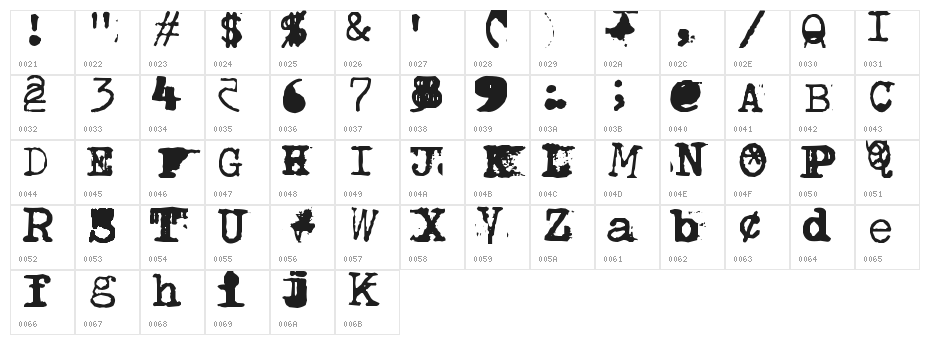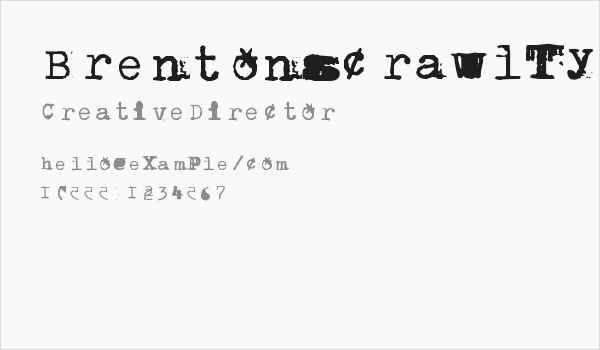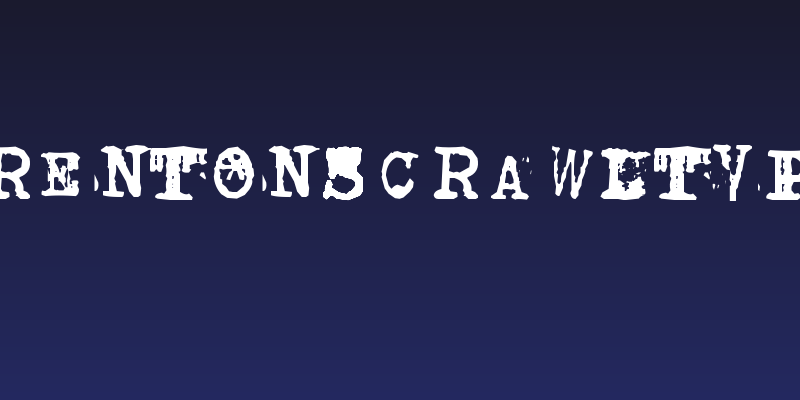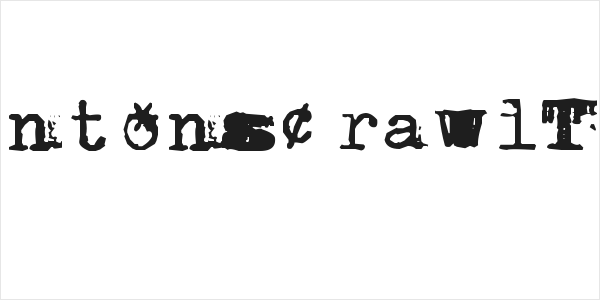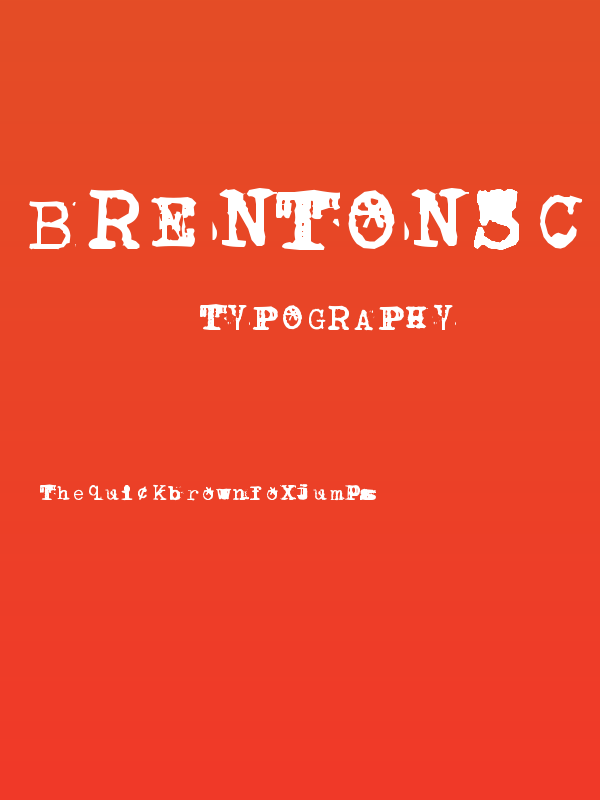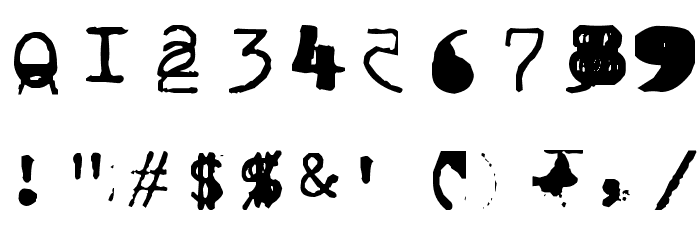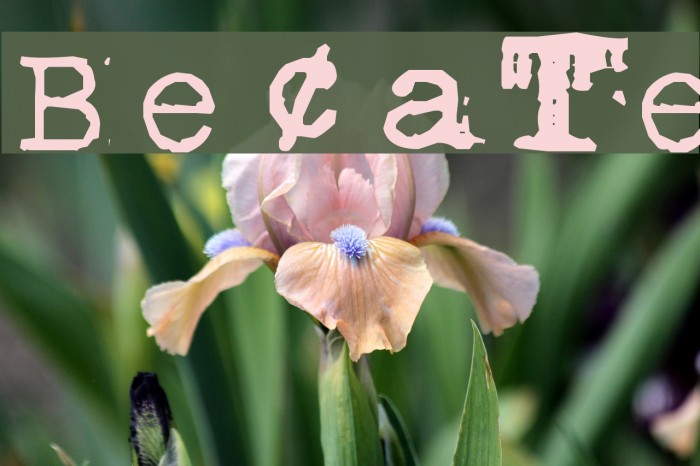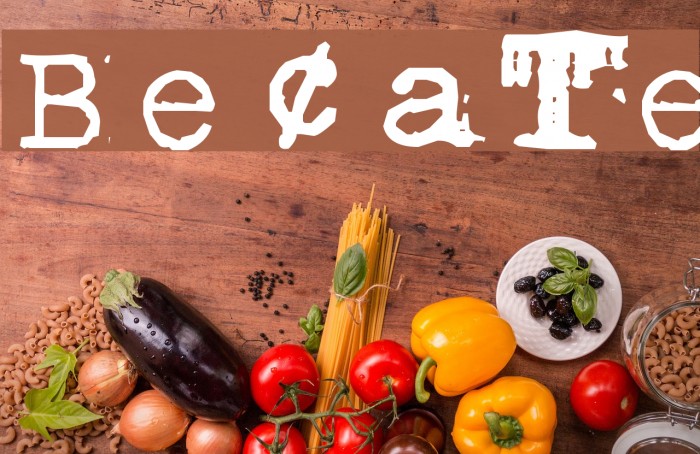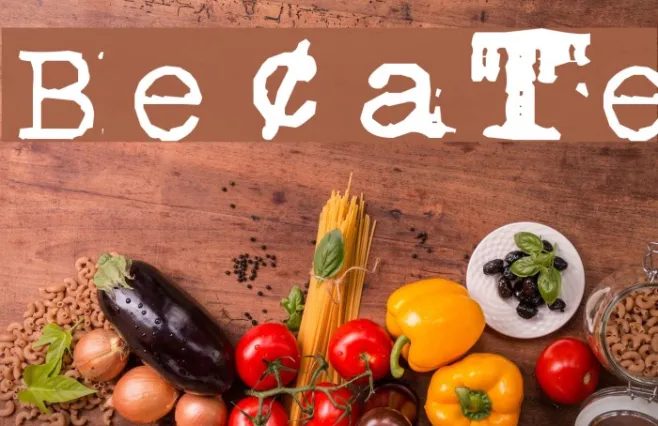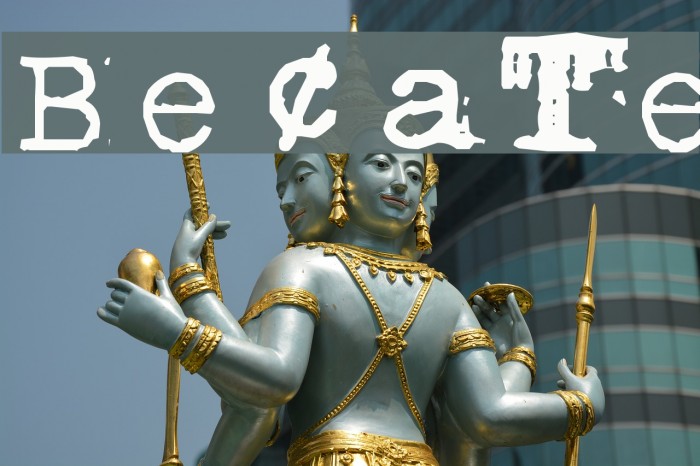
BrentonscrawlType Font
✎ Quirky
| Gesamtstil | Vintage, Grunge |
| Anwendungsfall | Headlines, Artistic projects, Creative branding |
| Vorgeschlagene Projekte | Ideal for vintage posters, album covers, artistic projects, and creative branding. |